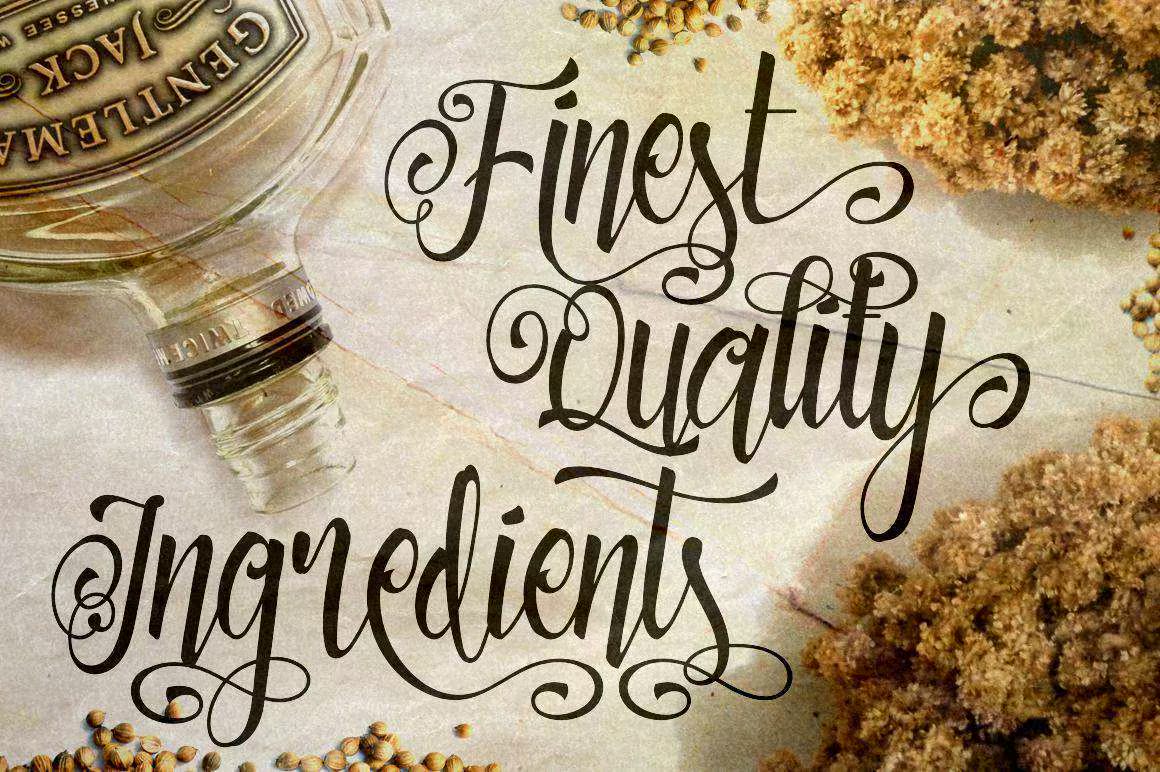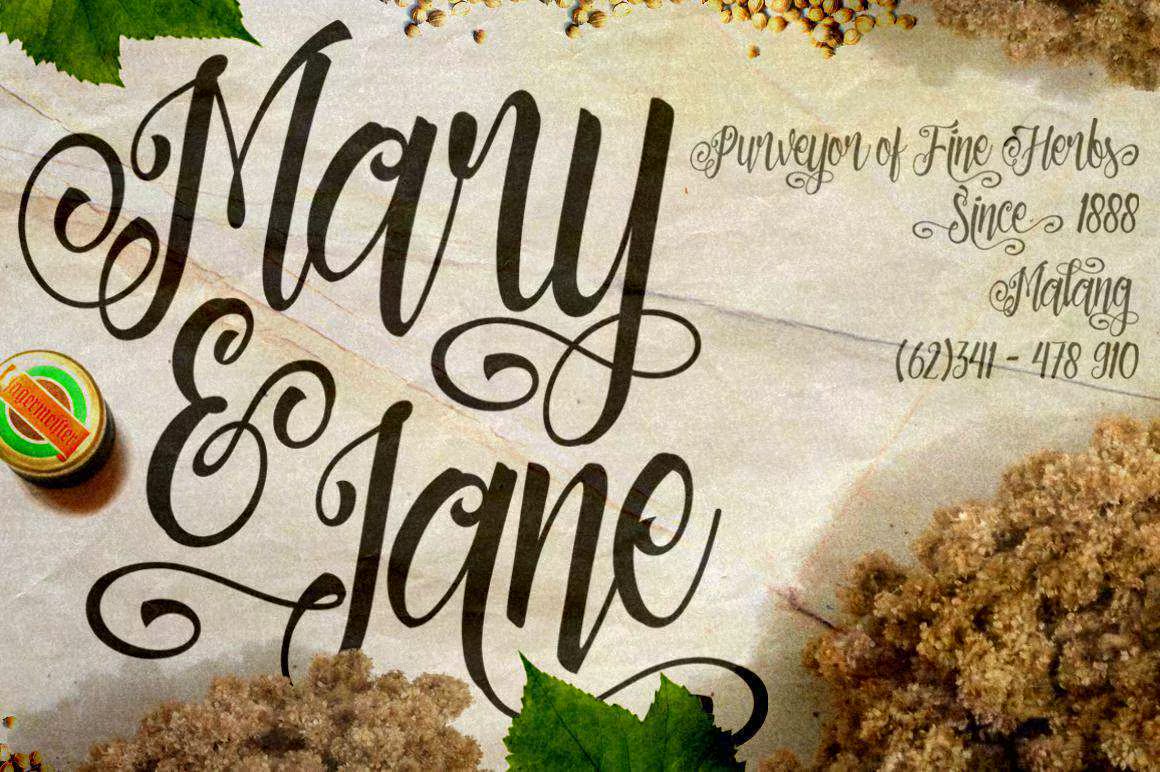
赞助人手稿是一种结合了线条和细线、放松和收紧以及独特的基线组合的手写字体。适合您的设计项目;Wedding Vitation、t-Shirt设计、FancylogType等。该字体带有+300个字形。用户可在结合了细线、松线和紧线以及基线组合的螺旋脚本字体面上书写匆匆字体,以获得更好的手感。适合您的设计项目;weddinginvitation、t-shirtdesign、fancylogotype等。此字体包含+300个字形。